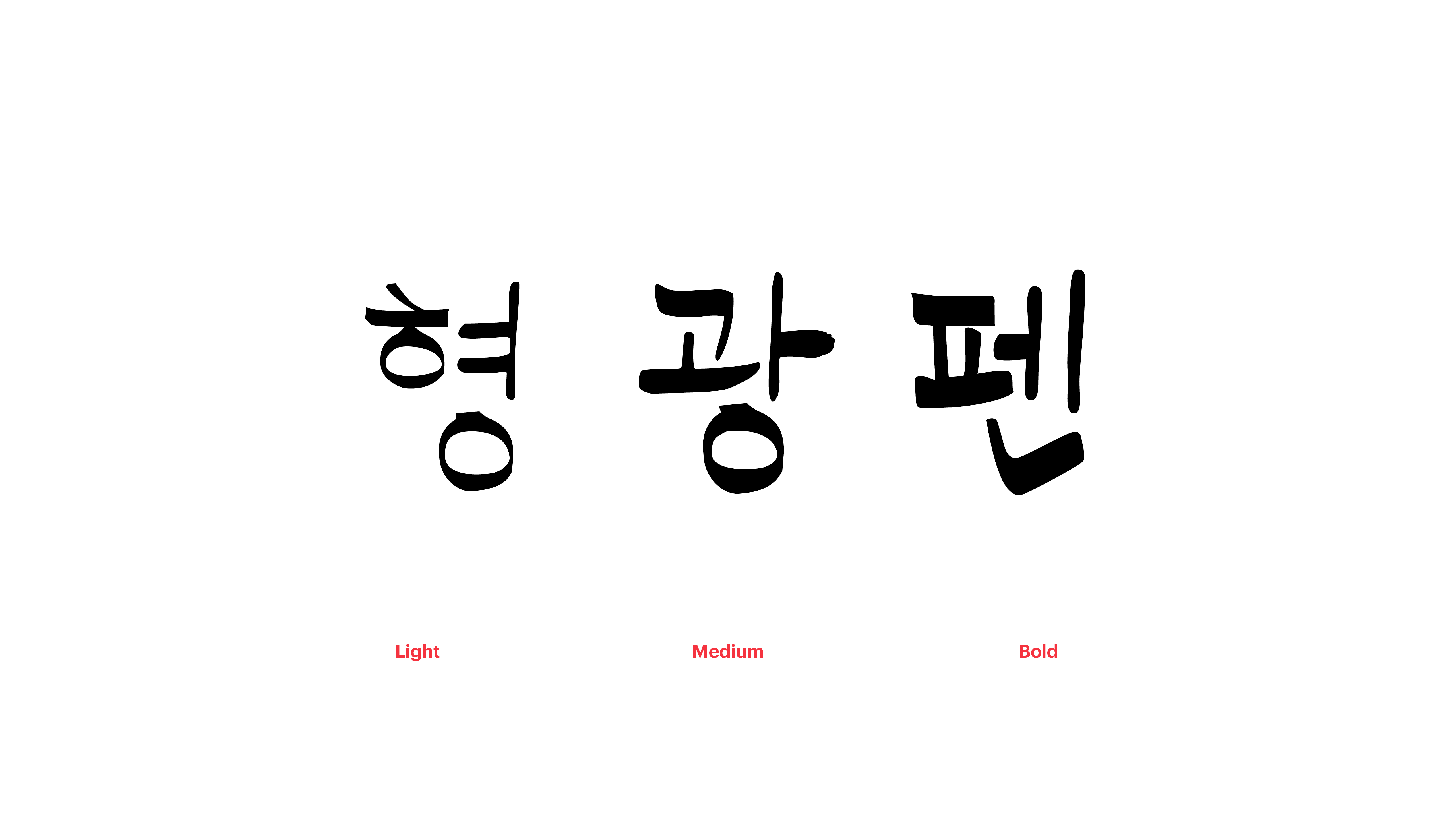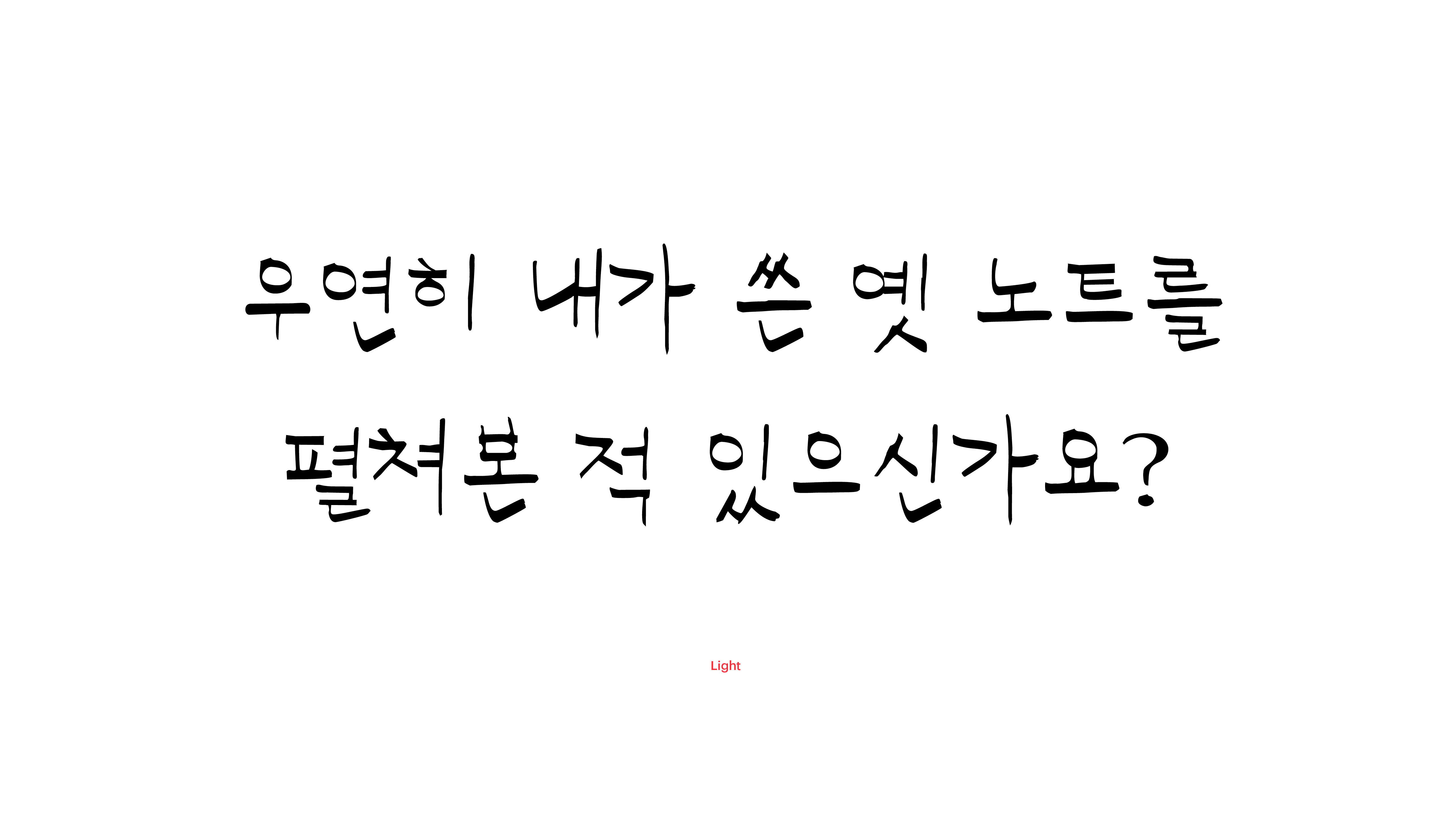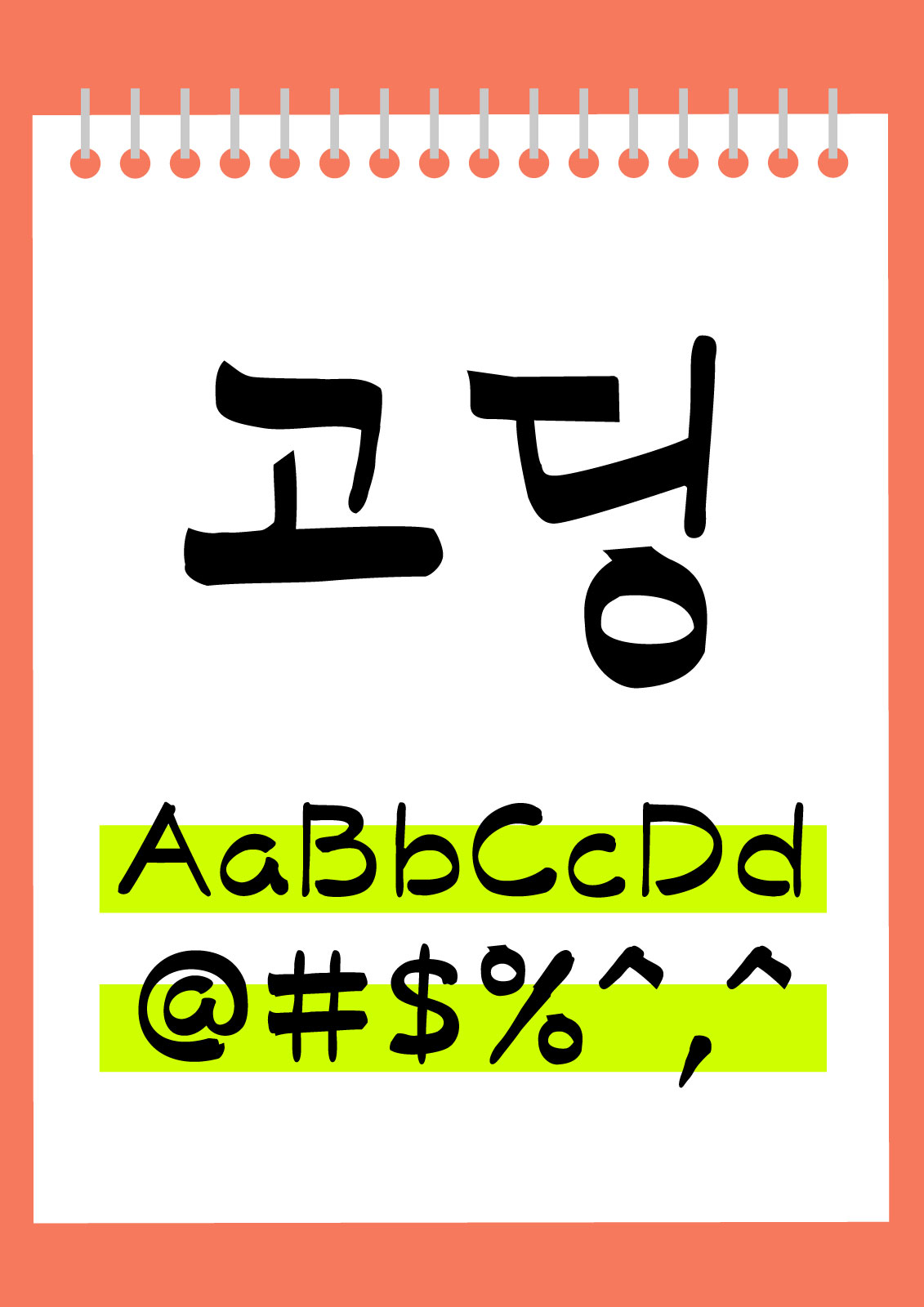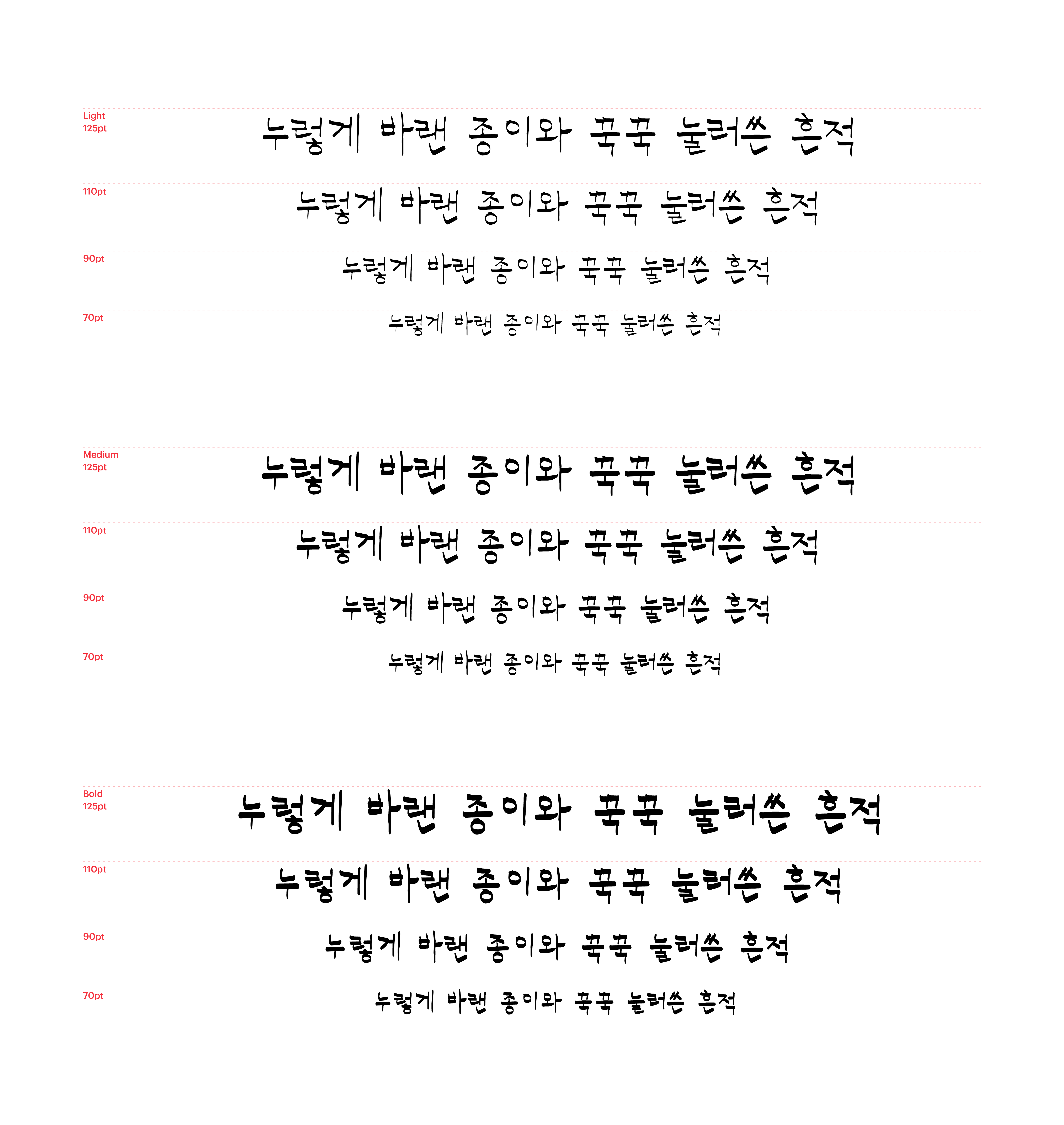
고딩
Yoon 고딩
우연히 내가 쓴 옛 노트를 펼쳐본 적 있으신가요? 누렇게 바랜 종이와 꾹꾹 눌러쓴 흔적이 선사하는 아련함. 고딩체에는 그 시절의 맑고 투명한 감성이 담겨 있습니다. 자연스러운 펜 손글씨 이미지를 섬세한 곡선으로 표현하는 동시에 질서정연하게 정돈해, 가지런하면서도 따뜻한 기분을 선사한답니다.